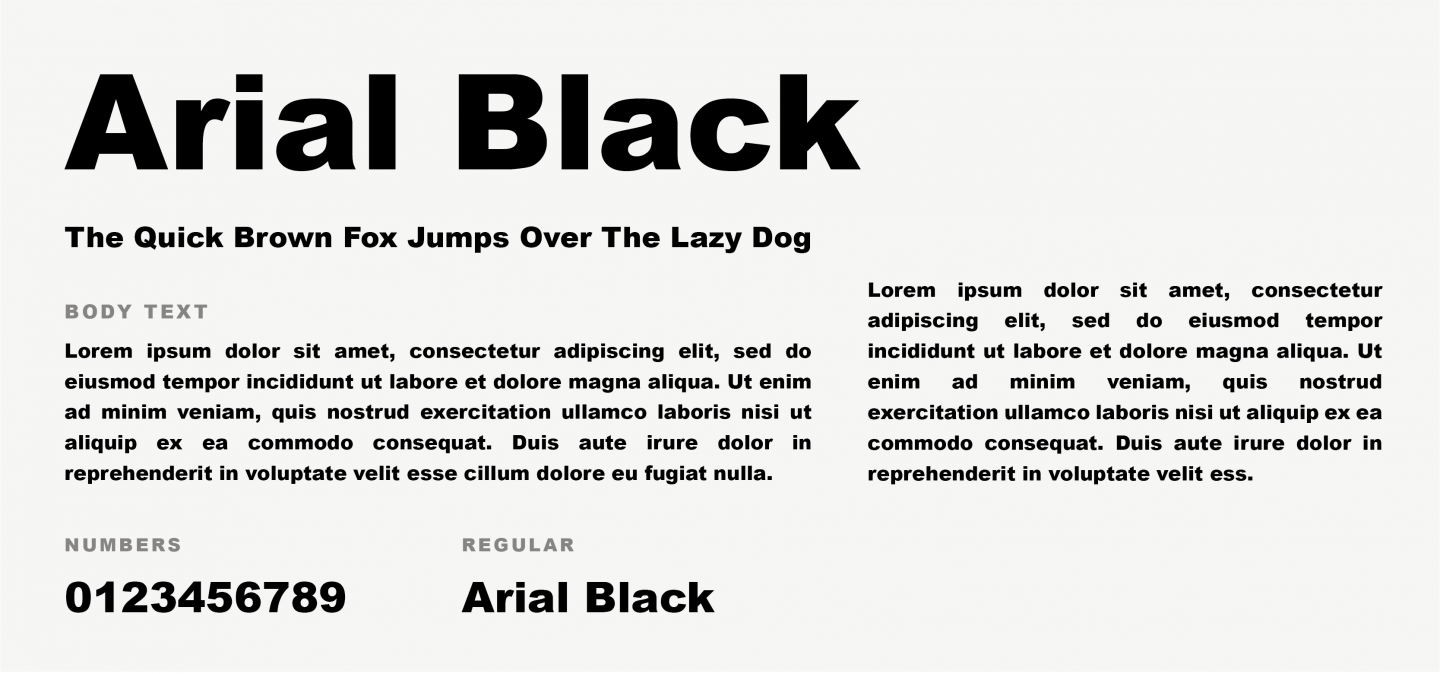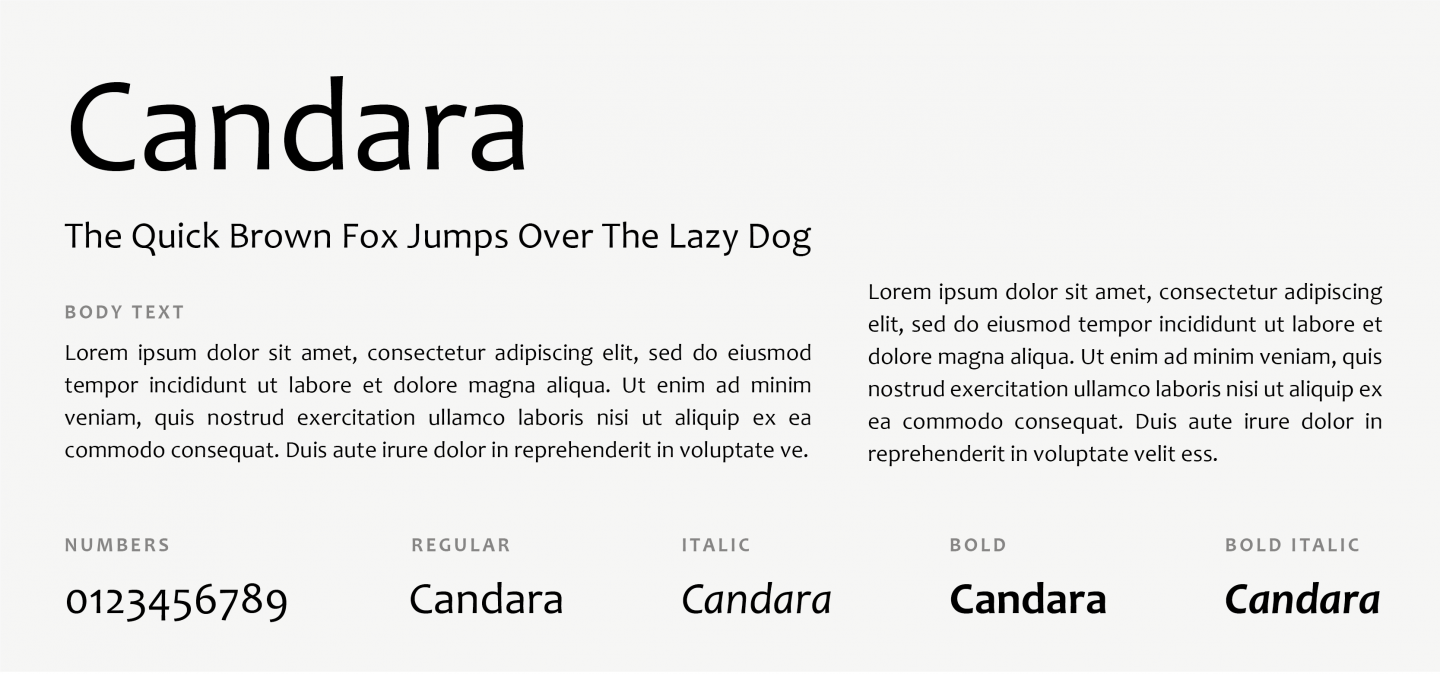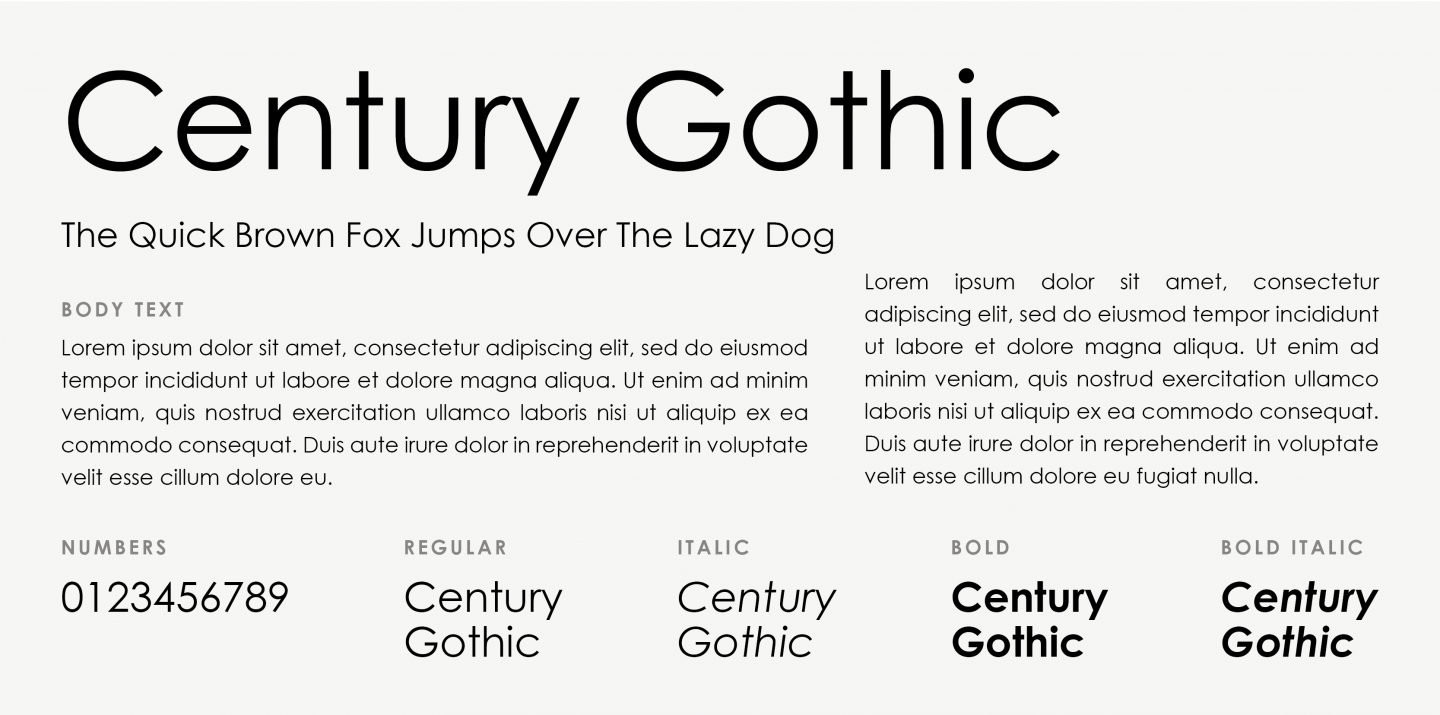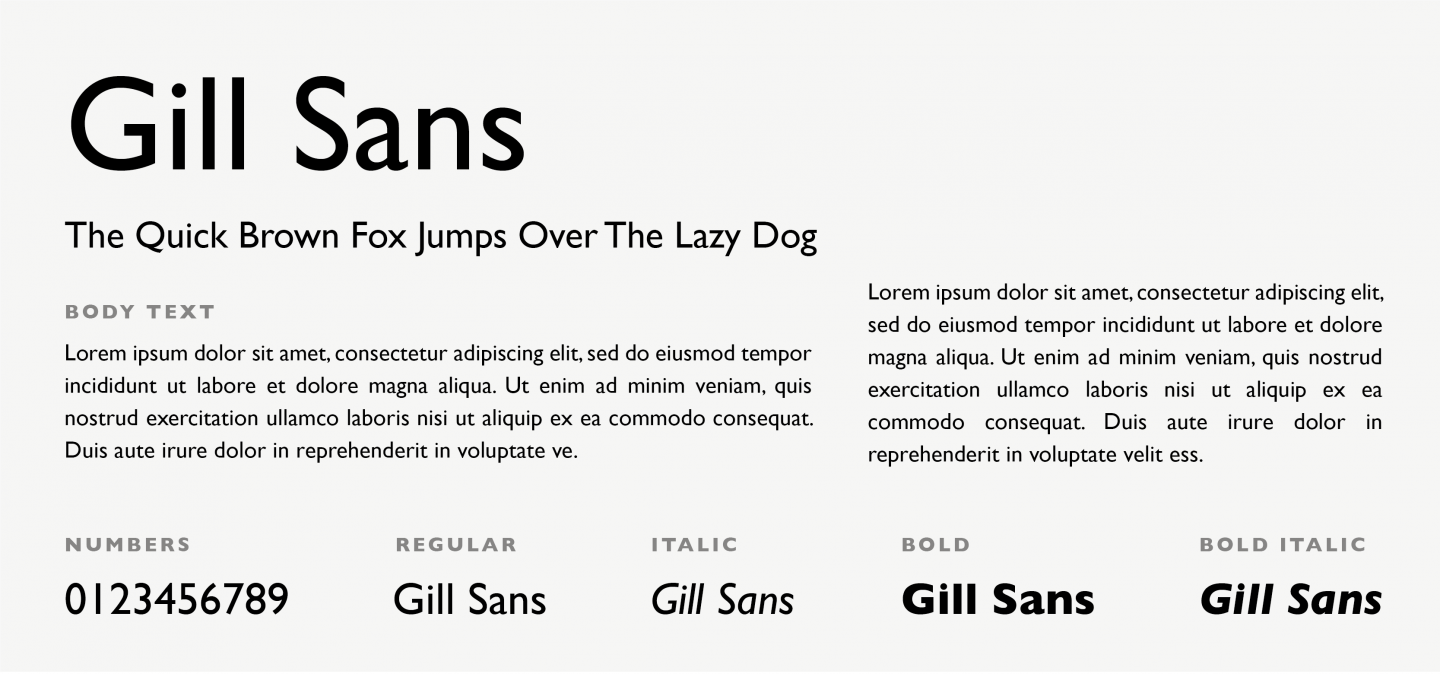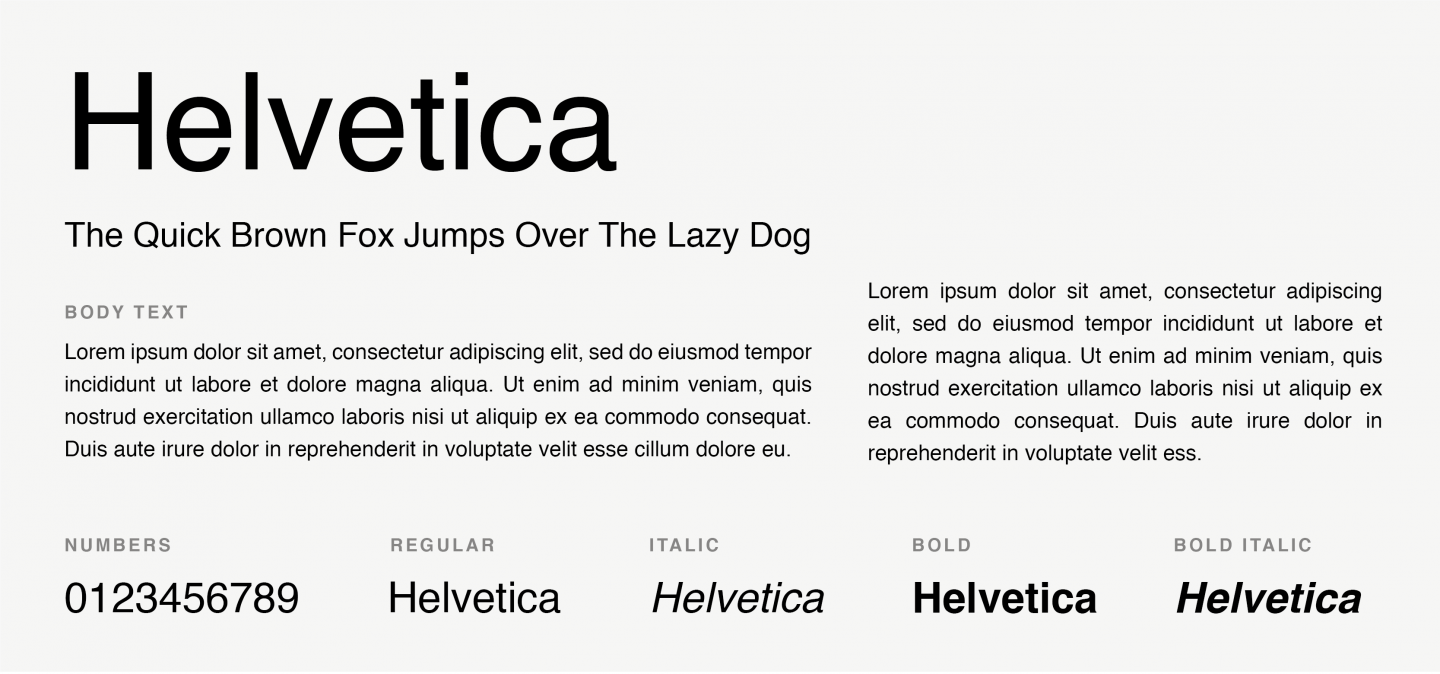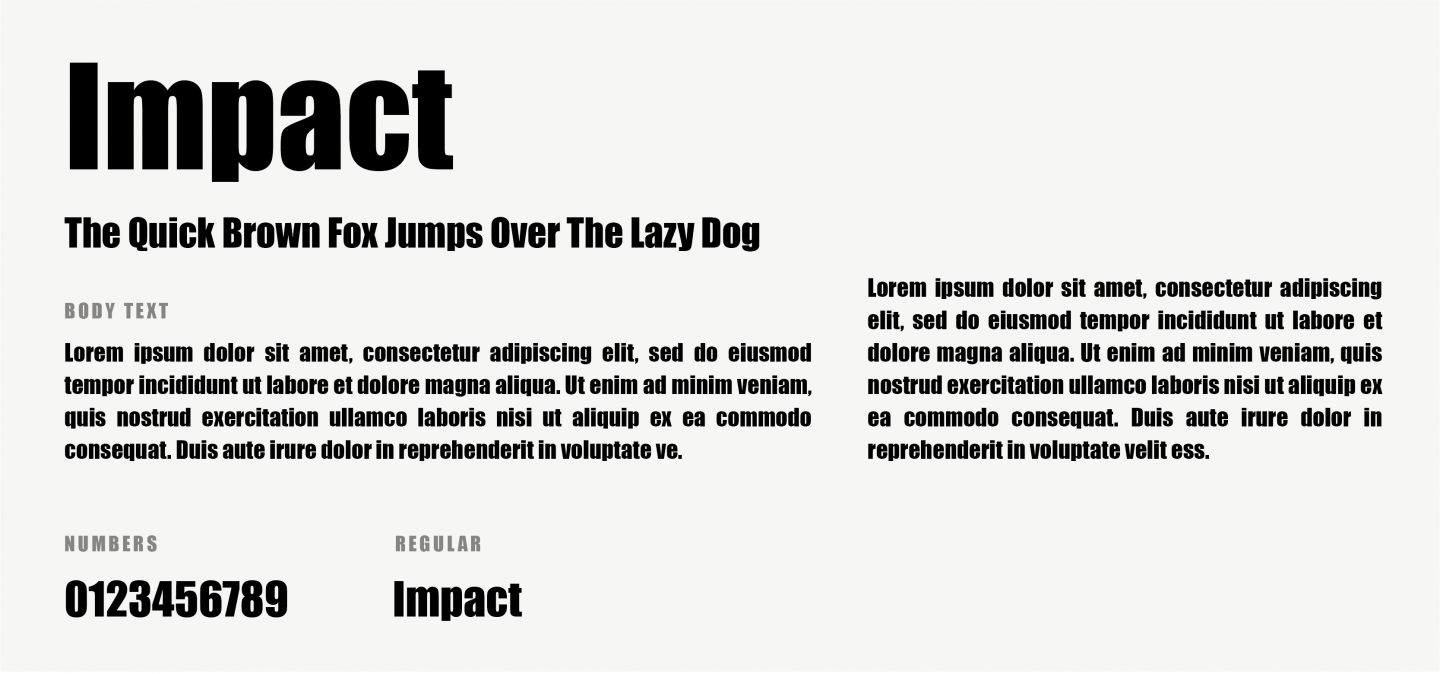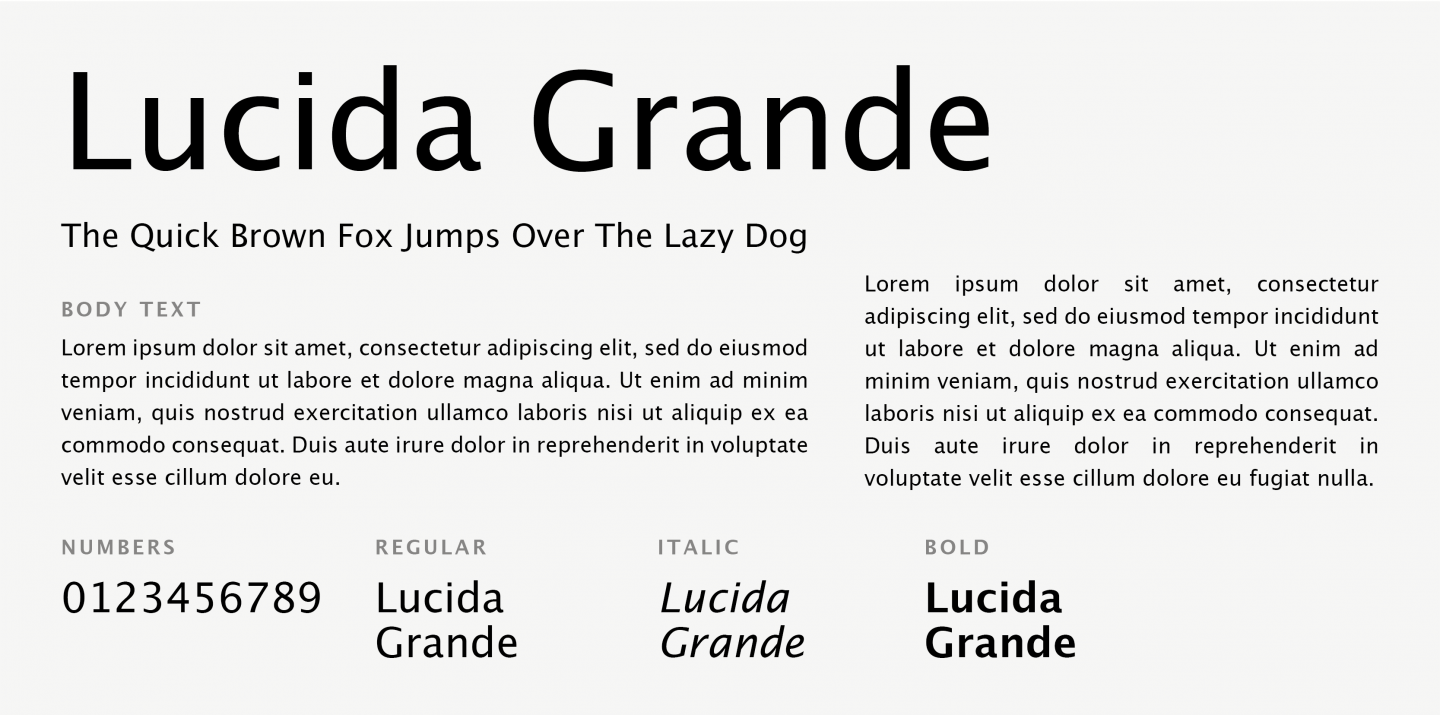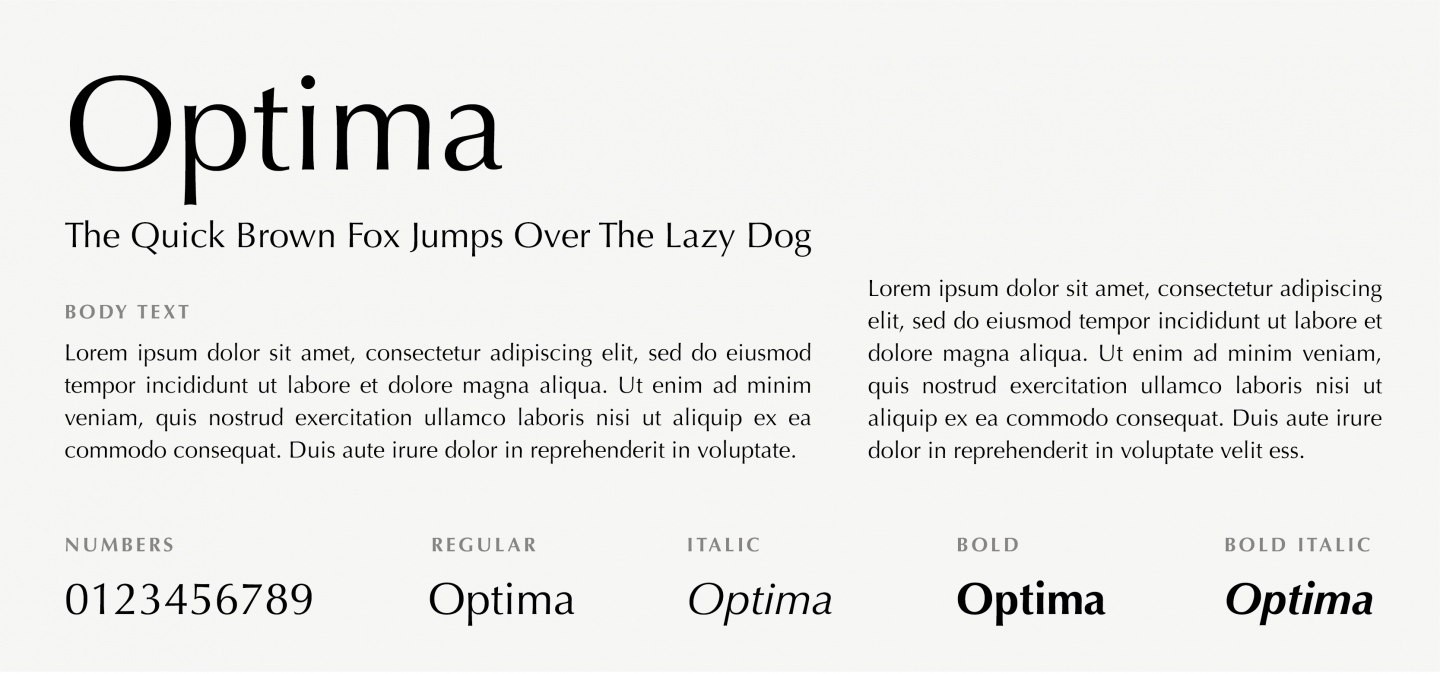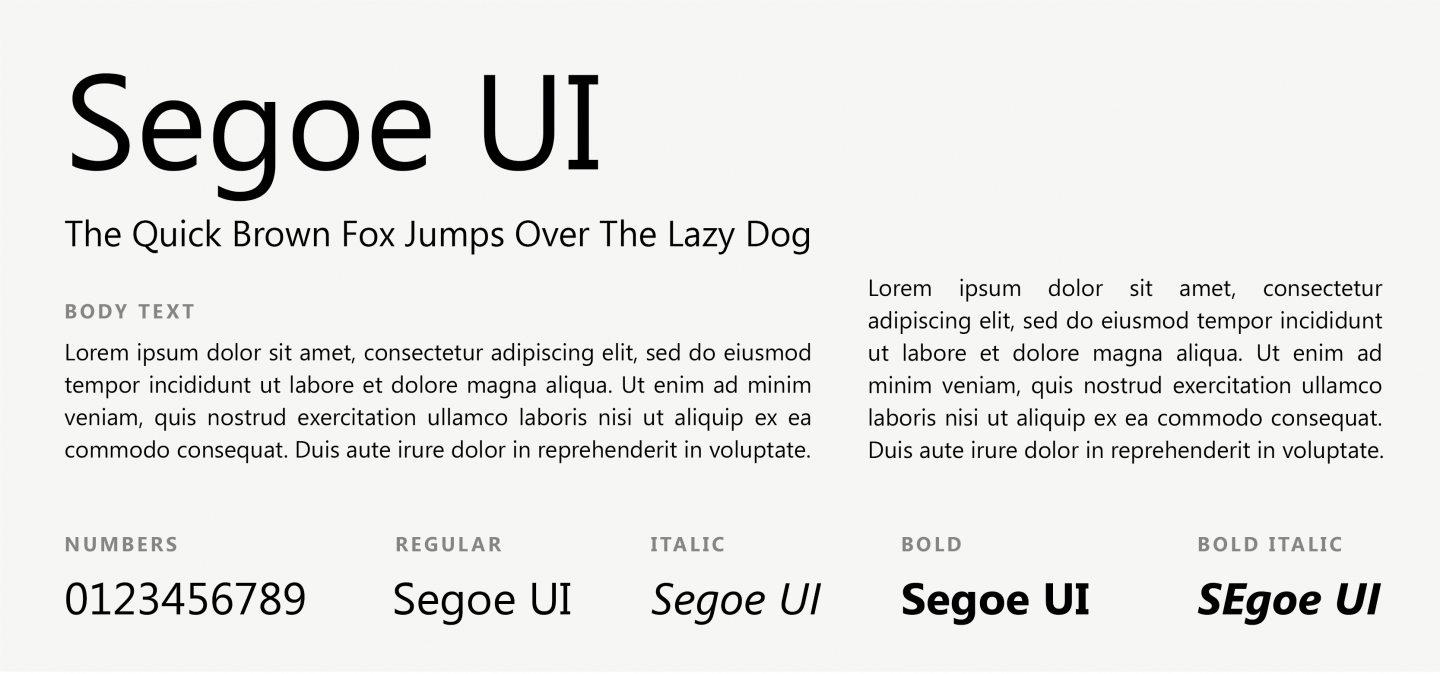
33 de fonturi uimitoare sigure pentru web și de ce aveți nevoie de ele!
Publicat: 2020-12-15Să recunoaștem, toți am fost acolo. Proiectezi un site web și vrei să fii cât mai creativ posibil și asta include utilizarea unor fonturi uimitoare! Cu toate acestea, când vine vorba de tipografie, există câteva restricții pe care ar trebui să le luați în considerare înainte de a vă stabili fonturile pentru site-ul dvs. WordPress. De ce? Alegeți-o pe cea greșită și puteți constata că nu se va afișa corect pentru toți vizitatorii site-ului.
La urma urmei, folosirea unei tipografii creative și unice pe design-ul site-ului tău web nu este de nici un folos dacă fontul pe care l-ai ales nu poate fi încărcat și este înlocuit cu un font aleatoriu de sistem, care îți strică complet modelele frumoase, nu-i așa?
Acesta este motivul pentru care este recomandat să alegeți un așa-numit Font Web Safe pentru modelele dvs.
Să luăm asta de la început și să aflăm mai multe despre fonturile Web Safe și apoi să ne uităm la 33 dintre cele mai bune fonturi Web Safe pe care le poți folosi pentru site-ul tău WordPress!
Ce înseamnă „Fonturi sigure pentru web”?
Fonturile Web Safe sunt fonturi care sunt preinstalate universal pe toate dispozitivele. Ele nu trebuie să fie descărcate de pe serverul site-ului web ca și restul activelor site-ului web pentru a fi afișate. Acest lucru vine cu două beneficii majore:
- Vă puteți aștepta ca tipografia care implică fonturi Web Safe să apară exact așa cum este destinată majorității utilizatorilor. Dacă totuși, nu utilizați un font Web Safe și acel font nu este instalat pe computerul unui utilizator și din anumite motive nu poate fi descărcat, site-ul dvs. web va reveni la un font de sistem, ceea ce nu numai că vă va distruge designul și branding vizual, dar uneori chiar ajung să fie imposibil de citit.
- Fonturile Web Safe sunt stocate local, astfel încât site-ul dvs. ar trebui să se încarce mult mai repede. Aceasta înseamnă o viteză și o performanță mai bune, ceea ce va avea un impact pozitiv asupra eforturilor dvs. de SEO, deoarece viteza de încărcare a paginii este unul dintre factorii luați în considerare pentru clasarea paginii.
Așadar, aproape fără excepție, ar părea să aibă sens să folosești întotdeauna un font Web Safe pentru design-ul site-ului tău web. Dar, chiar dacă decideți că doriți să sacrificați o parte din performanța site-ului dvs. pentru probleme de coerență a mărcii și să utilizați tipul de caractere al mărcii dvs., ar trebui să proiectați întotdeauna ținând cont de fonturile Web Safe. De ce este asta? Pentru că vor exista cazuri în care fontul dvs. nu va fi descărcat și afișat corect (browsere mai vechi sau conexiune la internet slabă, de exemplu).
În aceste cazuri, este bine să aveți un Plan B, o opțiune de rezervă pentru atunci când prima opțiune ar putea să nu funcționeze. Chiar dacă lista de fonturi Web Safe nu este lungă, puteți găsi cu siguranță unul foarte asemănător cu opțiunea dumneavoastră originală. În acest fel, puteți avea control 100% asupra modului în care site-ul dvs. va fi afișat pentru toți utilizatorii și nu veți risca să apară Times New Roman (ca un substitut de font aleatoriu) și să vă strice site-ul frumos proiectat!
Dar Google Fonts?
Fonturile Google sunt adesea confundate cu fonturi Web Safe. Nu este chiar așa însă. Fonturile Google nu sunt preinstalate pe un dispozitiv, ci sunt găzduite de Google. Deci, pentru ca acestea să fie afișate pe computerul unui vizitator al site-ului, fișierele cu fonturi trebuie mai întâi descărcate la fel ca orice alt material. Acest lucru le afișează automat ca Fonturi web și de aceea sunt atât de des confundate cu „Fonturi sigure pentru web”.
Cu toate acestea, fonturile oferite de API-ul Google Fonts sunt comprimate automat pentru o descărcare mai rapidă și, odată descărcate, sunt stocate în cache în browser și reutilizate de orice altă pagină web care utilizează API-ul Google Fonts. Pur și simplu, acestea sunt descărcate mult mai rapid și vor avea mult mai puțin efect asupra vitezei și performanței site-ului dvs. web. Așadar, chiar dacă nu sunt strict fonturi Web Safe, ele sunt totuși perfect sigure pentru a fi utilizate pe site-ul dvs. web și pot ajuta să îi confere un aspect mai unic și creativ.
Notă: deși folosirea fonturilor Google este considerată o alegere „sigură” și populară pentru design web, este totuși foarte recomandat să proiectați ținând cont de fonturi sigure pentru web, așa cum am menționat anterior. Alegeți întotdeauna un font sigur pentru web, aproape de alegerea dvs. principală, în care fonturile dvs. vor „reduce” dacă este necesar.
Puteți să răsfoiți și să vă inspirați pentru următorul proiect, vizitând Fonturile Google.
Care sunt cele mai bune fonturi sigure pentru web?
Adevărul este că lista de fonturi Web Safe este mai scurtă decât și-ar dori un designer! Din fericire, sunt incluse unele dintre cele mai populare și bine concepute. Să aruncăm o privire, începând cu fonturile Sans-serif și trecând la familiile de fonturi Serif, Monospace și Cursive.
1. Arial
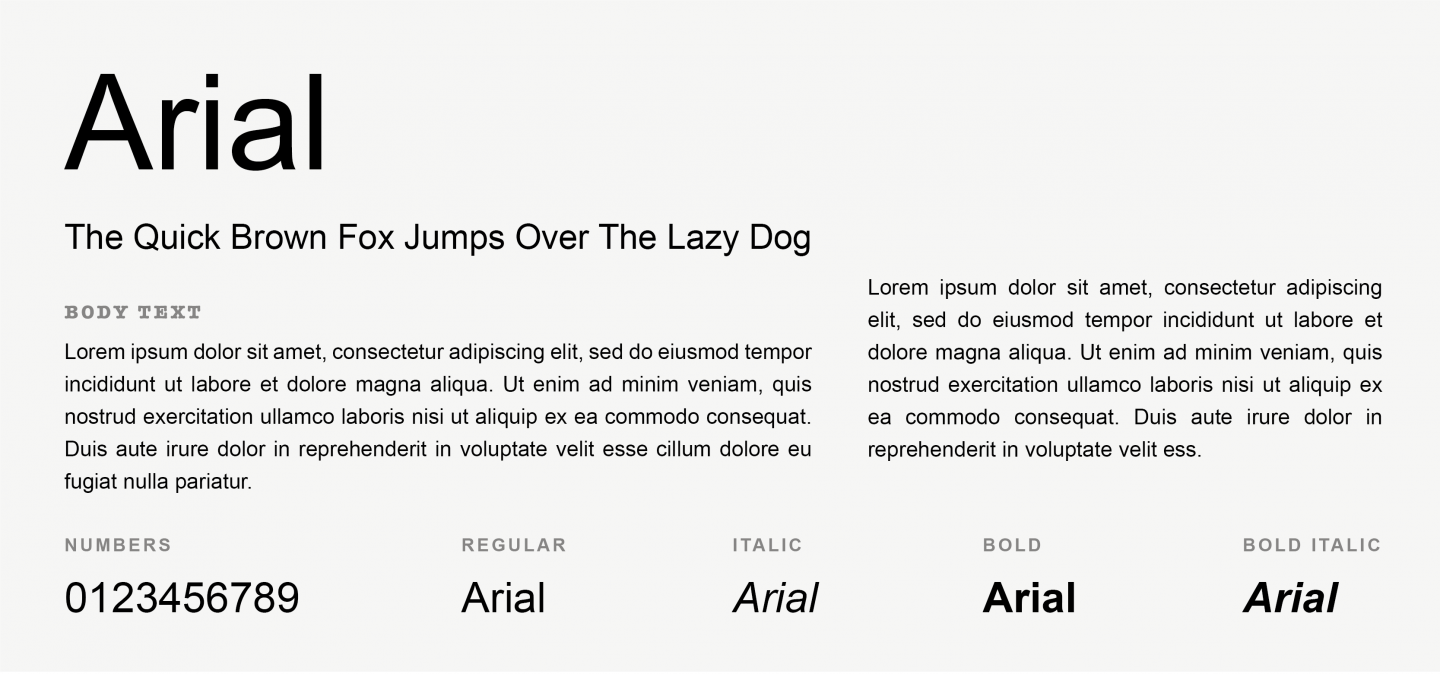
Concluzie
Alegerea tipografiei potrivite pentru a-ți reprezenta marca este o muncă grea.
Sperăm că acest articol v-a ajutat să înțelegeți de ce fonturile Web Safe sunt importante, fie ca opțiune principală, fie ca opțiune „de rezervă”, și cum să le utilizați pentru a vă asigura că desenele dumneavoastră arată bine pe orice dispozitiv.